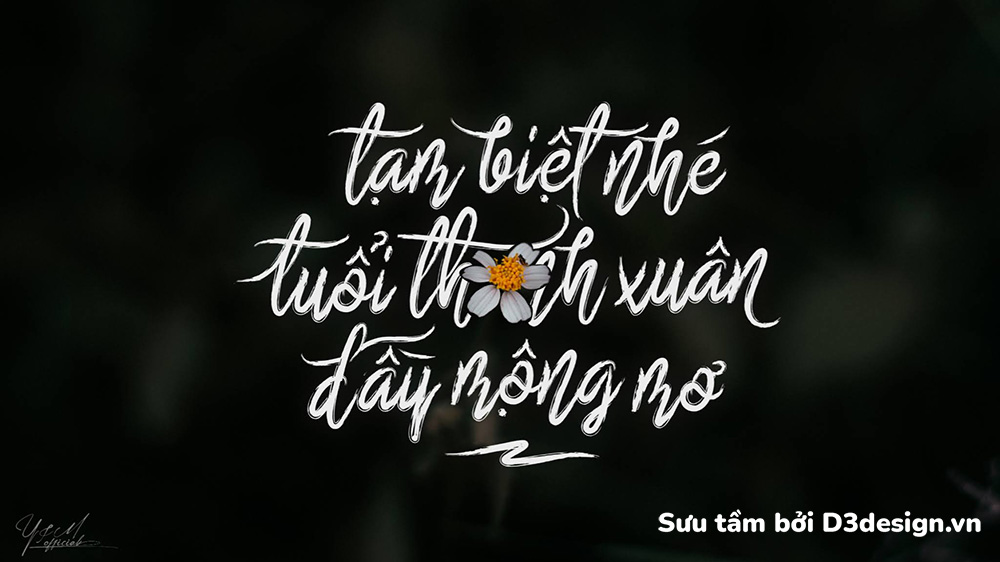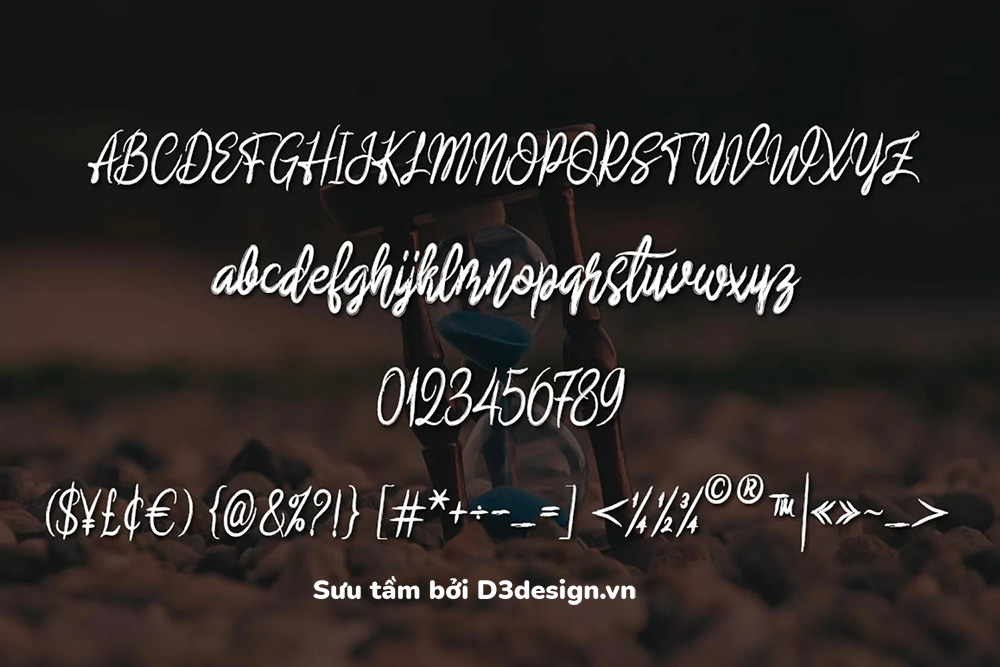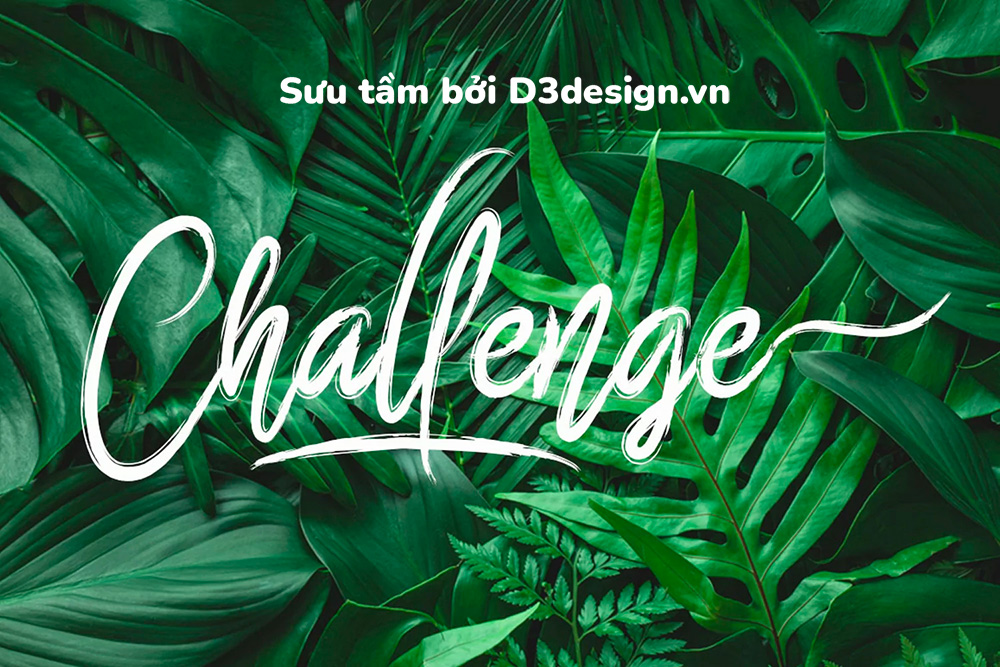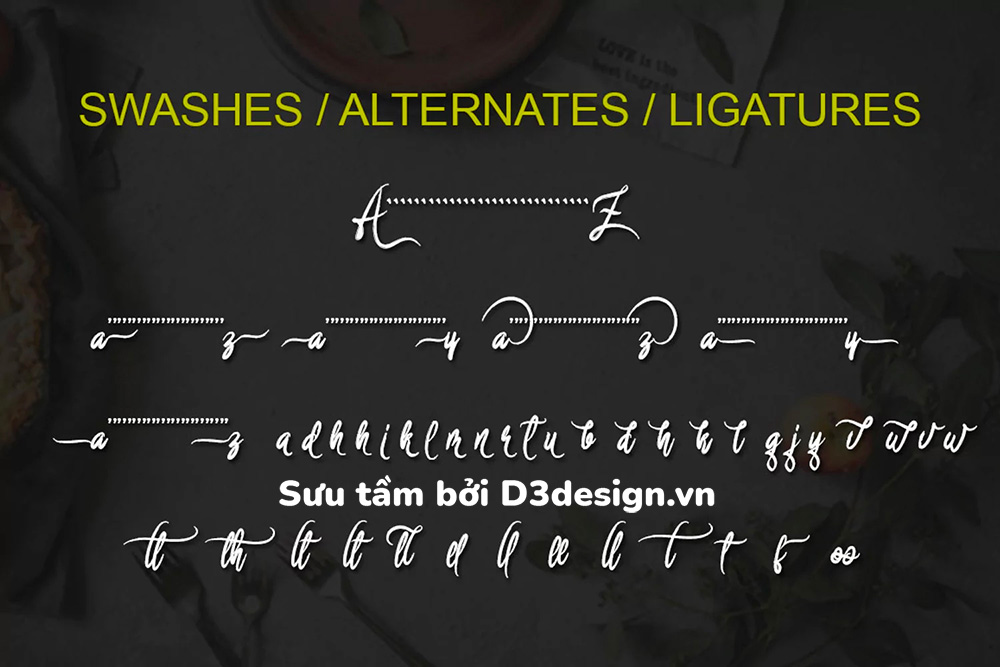
Font Việt Hóa - Fathan Nét Bút Lông Mang Phong Cách Cổ Điển
Fathan Việt Hóa một font chữ dạng bút lông thư pháp có đường nét đa dạng, đường nét thanh mảnh, nét cổ điển và thanh lịch. Có thể được sử dụng cho các mục đích khác nhau. Chẳng hạn như tiêu đề, chữ ký, logo, lời mời đám cưới, áo thun, tiêu đề thư, bảng tên, nhãn, tin tức, áp phích, huy hiệu, v.v.
Fathan hiển thị các ký tự thay thế thư pháp đầy phong cách. Bao gồm các chữ cái đầu tiên và thiết bị đầu cuối, các lựa chọn thay thế, chữ ghép và hỗ trợ nhiều ngôn ngữ. Font Fathan Việt Hóa bởi YM.